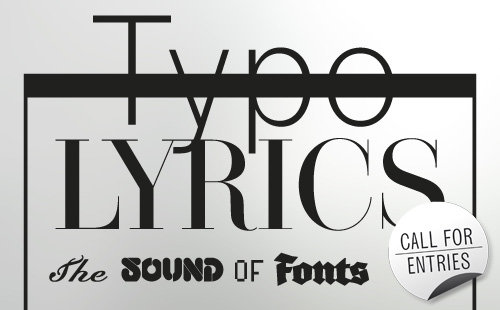
Die TypoLyrics verstehen sich als einzigartige Interaktion von Grafikdesign, Typografie und Musik. Wir wollen das Potential dieser außergewöhnlichen Schriftpräsentationen innerhalb eines neuen Buches zusammenführen und möchten Dich einladen, an diesem Projekt teilzunehmen!
Grafikdesigner lieben Musik. Unter anderem bestätigt dies das enorme Interesse, welches die Leser unseres Typo-Magazins Slanted der Rubrik TypoLyrics immer wieder schenken. Innerhalb dieser sind Gestalter aus aller Welt aufgerufen, zeitgenössische Schriften mittels Sogtexten zu ausdrucksstarken, bildhaften und illustrativen Präsentationen verschmelzen zu lassen. Wir veröffentlichen nun ein Buch welches den Namen der Slanted Reihe trägt – die TypoLyrics erscheinen im Mai 2010 beim renommierten Birkhäuser Verlag. ISBN 978-3-0346-0366-9
Analog zu der traditionellen Schriftklassifikationen ist das Buch in unterschiedliche Kapitel aufgeteilt. Jedes behandelt eine bestimmte Schriftgattung sowie Songs eines bestimmten Musikgenres. Wir stellen dir einen zur Schrift passenden Titel – drücke Play, lass dich inspirieren und deine Schrift rocken, swingen, tanzen, pogen ...